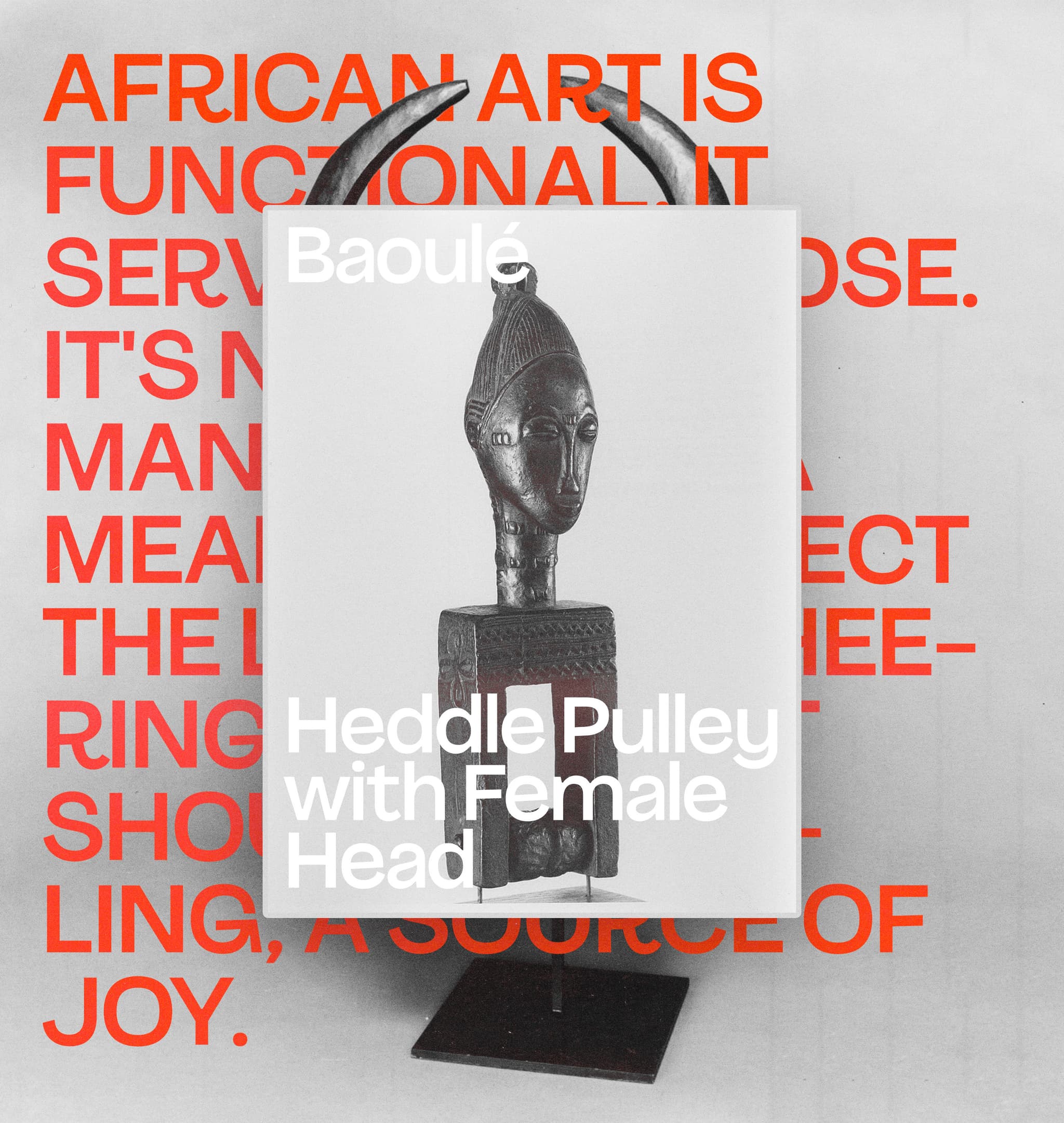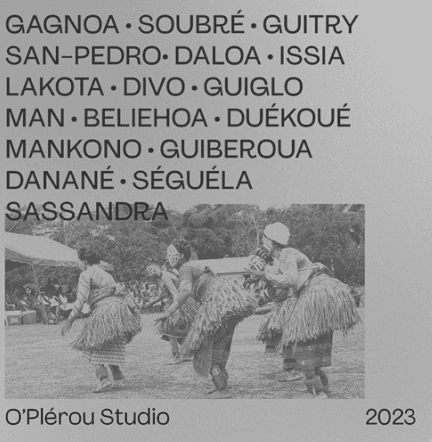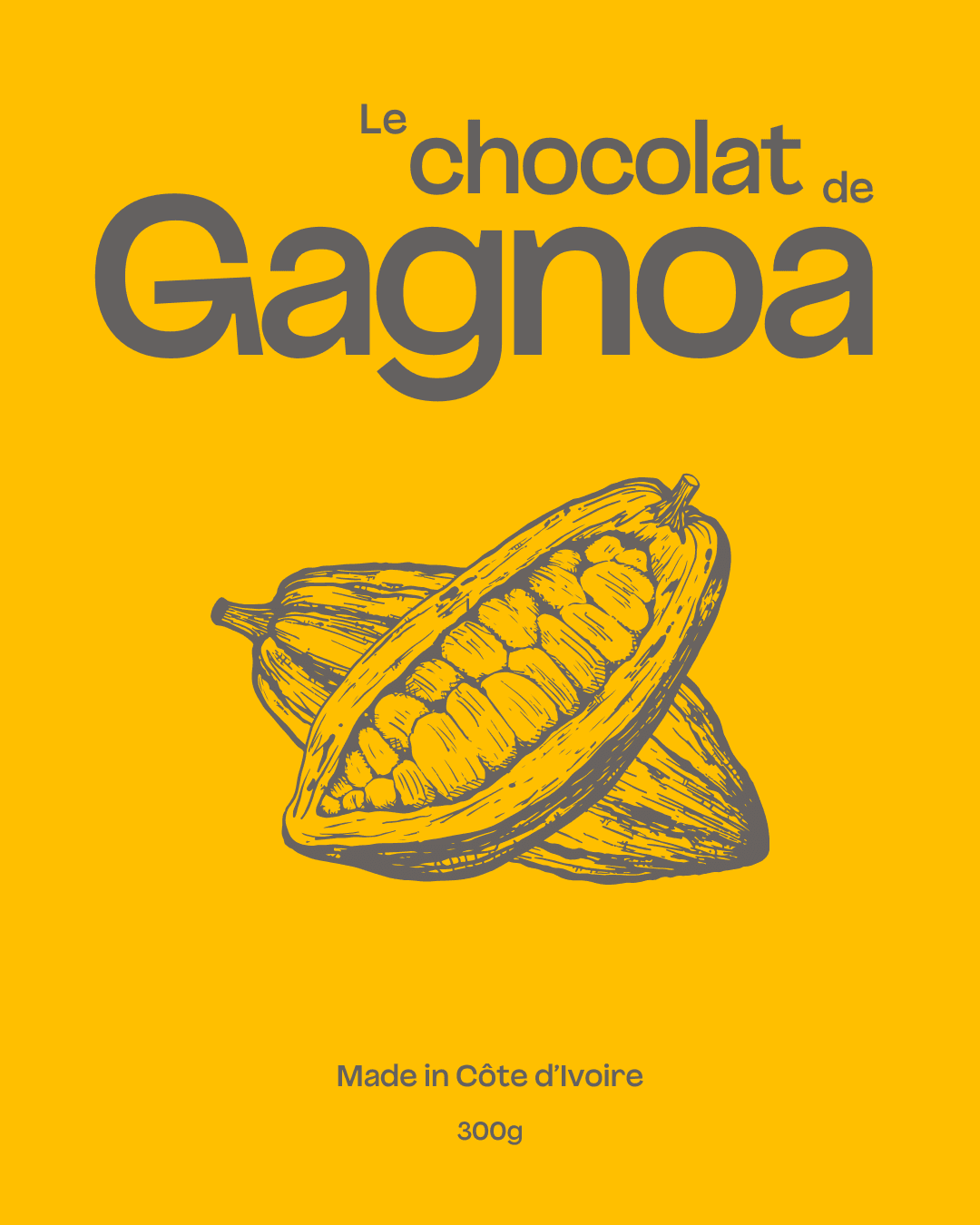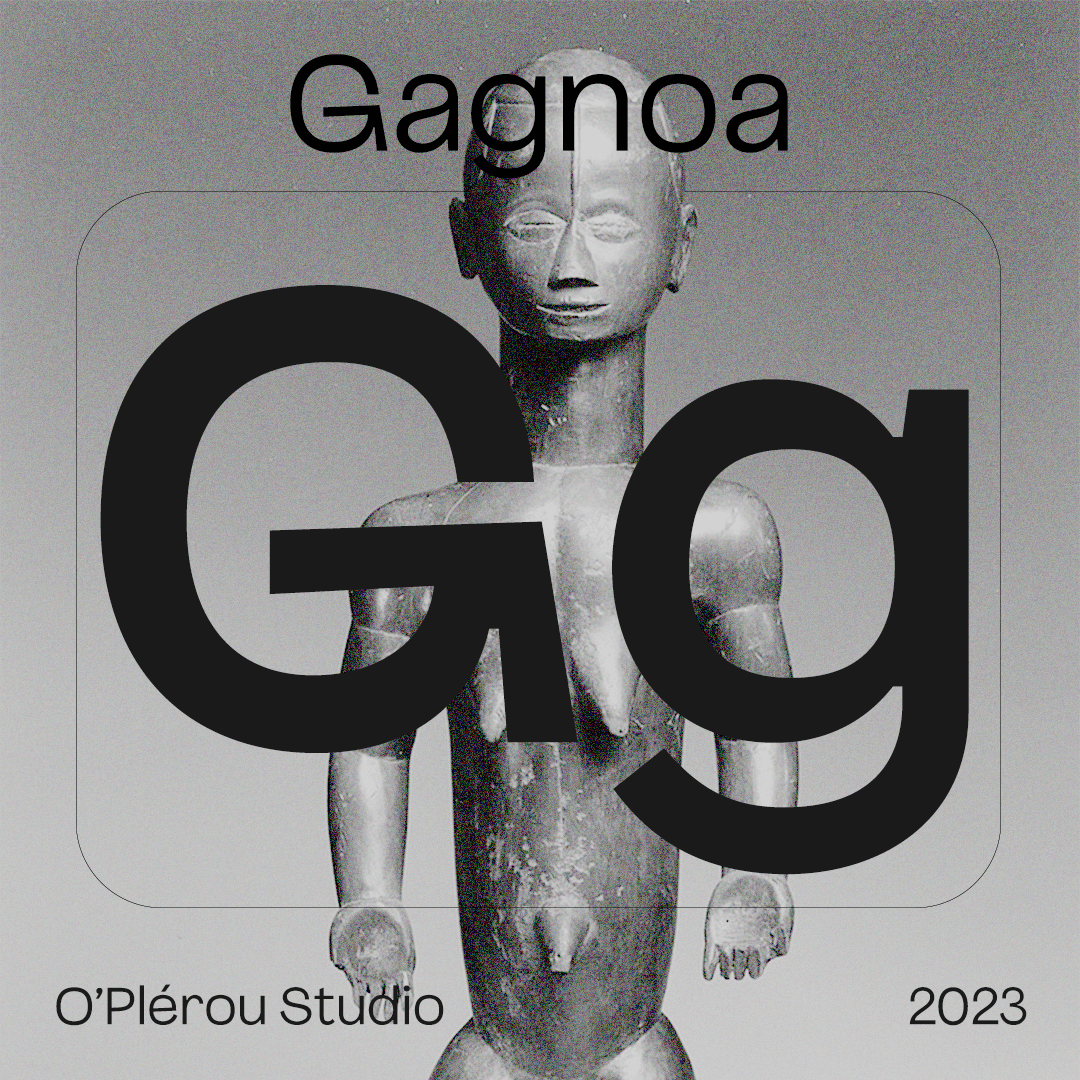
Le charme d'être soi.
Clear, distinctive and friendly.
Le charme d'être soi.
Clear, distinctive and friendly.
Be comfortable with your own kind of different
Certaines choses n'ont pas besoin d'en faire trop pour avoir du caractère. OS Gagnoa Core est une police de texte sans serif humaniste qui célèbre la beauté d'être humain. Ses proportions généreuses, ses formes rondes et ses détails singuliers apportent de la chaleur à la lecture sans détourner l'attention des mots. Ni mécanique ni excessivement expressive, Core trouve sa personnalité dans l'équilibre entre précision et singularité. Ses formes sont soigneusement construites, sans jamais effacer leur caractère. Des livres aux publications culturelles, en passant par les identités contemporaines et les compositions typographiques, Gagnoa Core donne aux mots une présence naturelle.